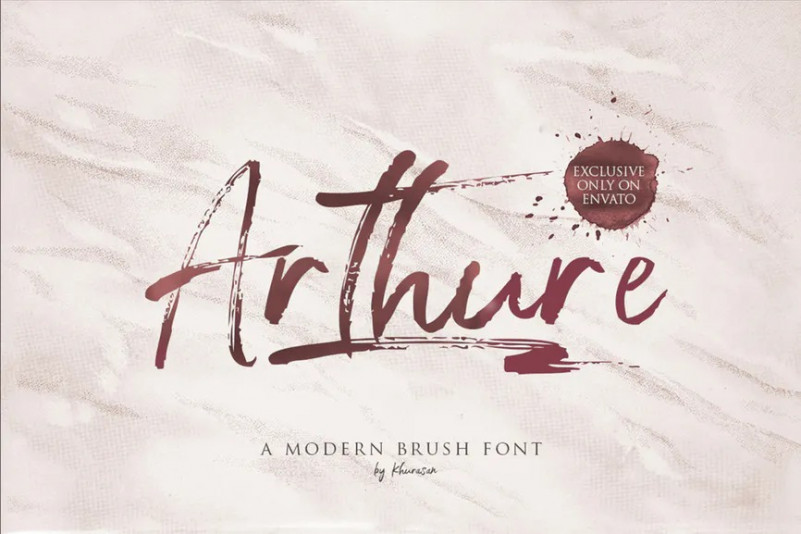
Arthure Font
L’ Arthure est une police de script manuscrite fraîche, élégante et moderne jeu de caractères. La police Arthure comprend un ensemble complet de lettres majuscules et minuscules, ainsi que le support multilingue, les croix gammées, les chiffres et la ponctuation.